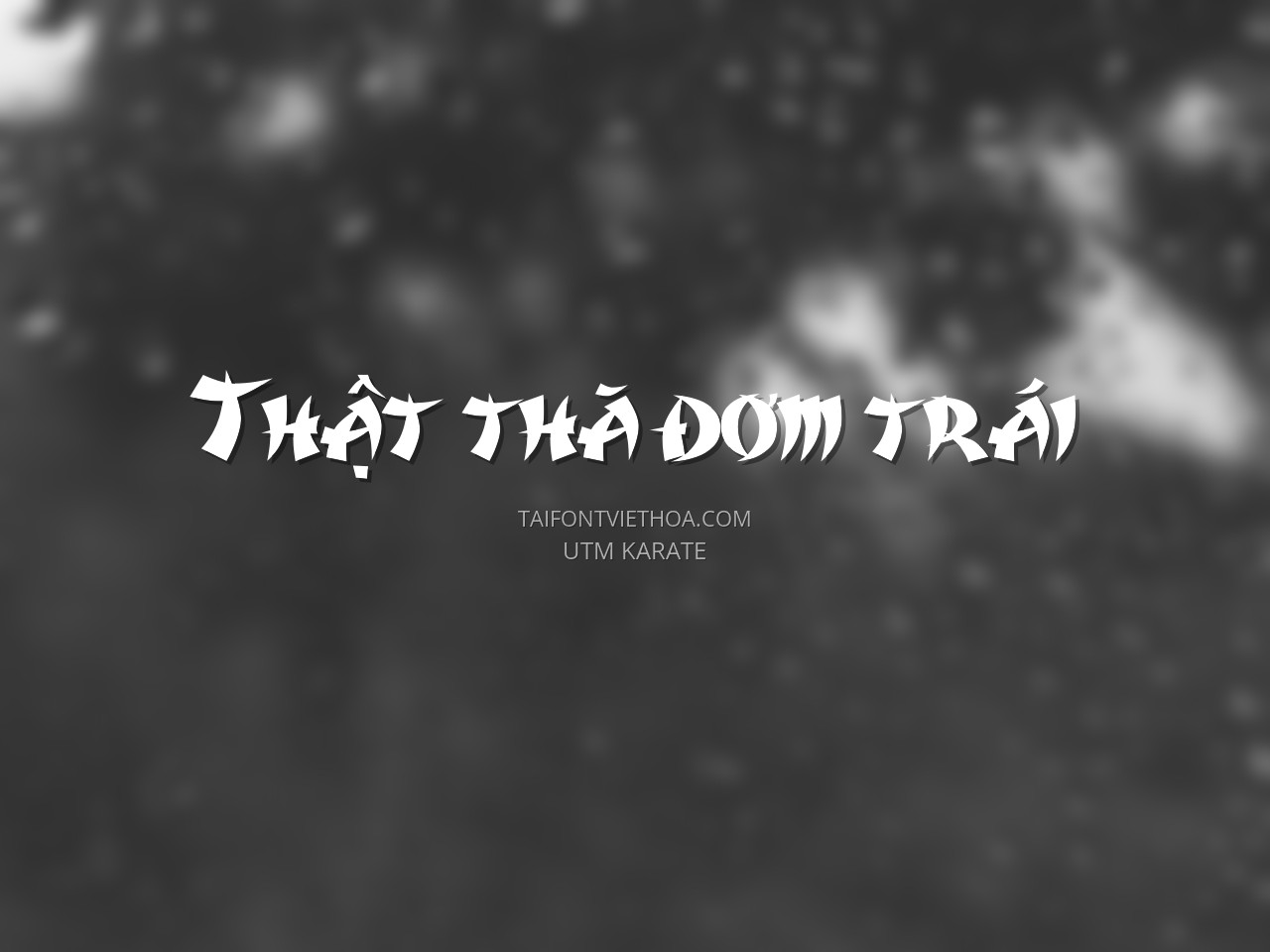
Font việt hóa UTM Karate
Giới thiệu về font UTM Karate
UTM Karate là phiên bản Việt hóa của font Karate – một kiểu chữ display mạnh mẽ, góc cạnh và đầy cá tính, lấy cảm hứng từ tinh thần võ thuật và phong cách thể thao năng động. Font gốc nổi bật với các nét chữ dày, sắc nét và thiết kế chắc chắn, rất phù hợp cho các dự án thiết kế cần sự ấn tượng và nổi bật. Phiên bản Việt hóa đã được hoàn thiện để hỗ trợ đầy đủ tiếng Việt cùng hơn 100 ngôn ngữ khác, mở rộng khả năng ứng dụng trong các dự án sáng tạo và quảng cáo đa dạng.
Đặc điểm thiết kế và ứng dụng của UTM Karate
UTM Karate sở hữu cấu trúc display với các nét chữ dày, góc cạnh và rõ ràng. Font có thiết kế chắc chắn, dễ đọc và tạo hiệu ứng thị giác mạnh mẽ, rất phù hợp cho tiêu đề, logo và các thiết kế cần sự ấn tượng. Font còn được trang bị nhiều ligature và glyph thay thế giúp tăng tính linh hoạt trong thiết kế.
Font thích hợp sử dụng trong thiết kế poster, bảng hiệu, nhận diện thương hiệu, quảng cáo, các dự án truyền thông đa phương tiện và nghệ thuật. Các ngành nghề phù hợp gồm: thể thao, giải trí, quảng cáo, thời trang và truyền thông sáng tạo.